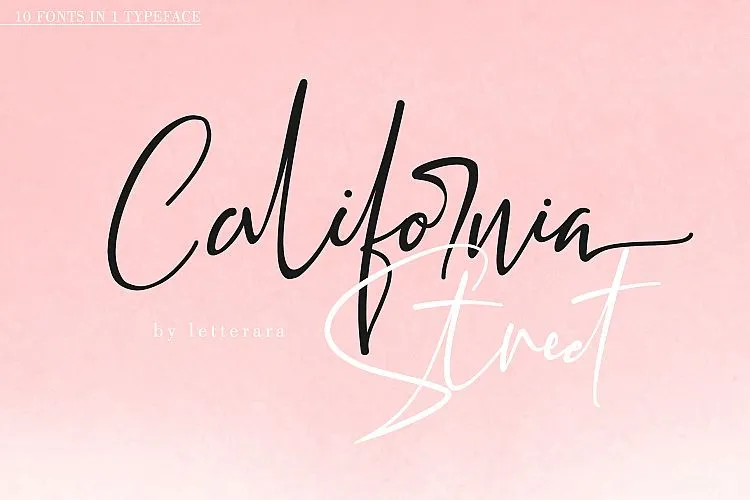
California Street Script Font – Download Grátis
A California Street Font é uma elegante fóntica cursiva com um toque real de escrita manuscrita. Ela tem um charme moderno e feminino, sendo perfeitamente apropriada para projetos que buscam uma leitura clara e sofisticada. Especialmente adequado para trabalhos que desejam adicionar um toque único e encantador ao design, esta fóntica é certamente um tesouro entre as opções de cursivas disponíveis. Feita por Daikian, a California Street Font oferece uma escrita suave e inocente, leve e encantadora. É ideal para quem busca uma fonte que seja perfeitamente elegante sem ser frívola ou exagerada. Com seu realismo na escrita manuscrita, esta fóntica irá tornar qualquer projeto especial, sejam eles cartazes de loja, identidades visuais de marcas, ou até mesmo as mais delicadas mensagens pessoais. É uma ótima opção para aqueles que procuram uma fonte que seja ao mesmo tempo moderna e romântica.
Designer: Daikian